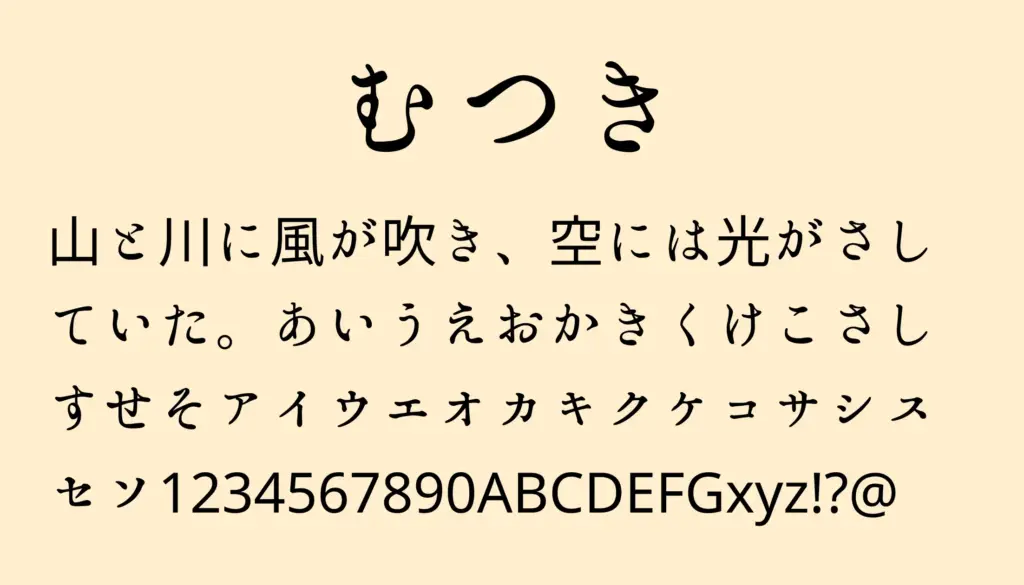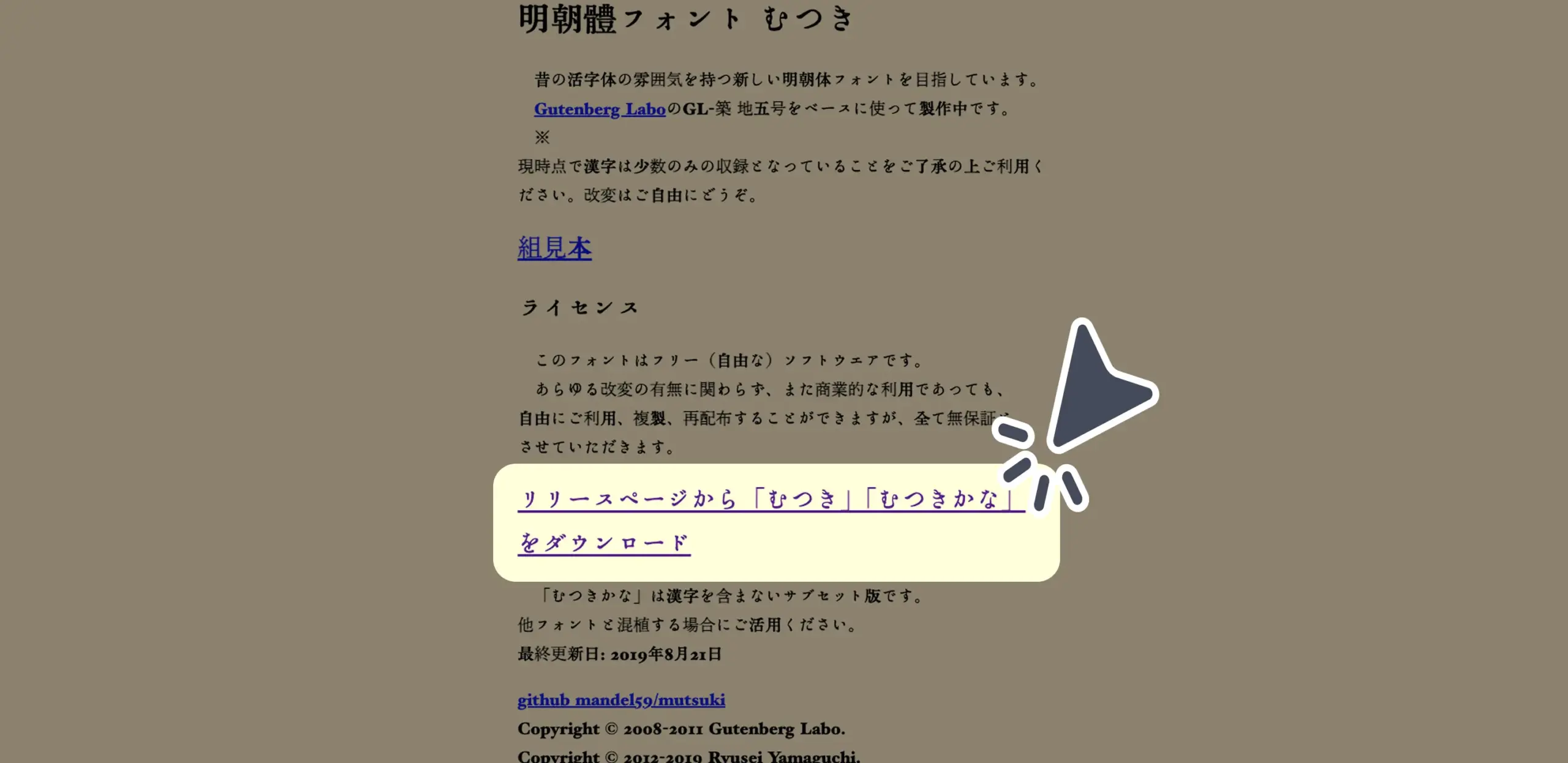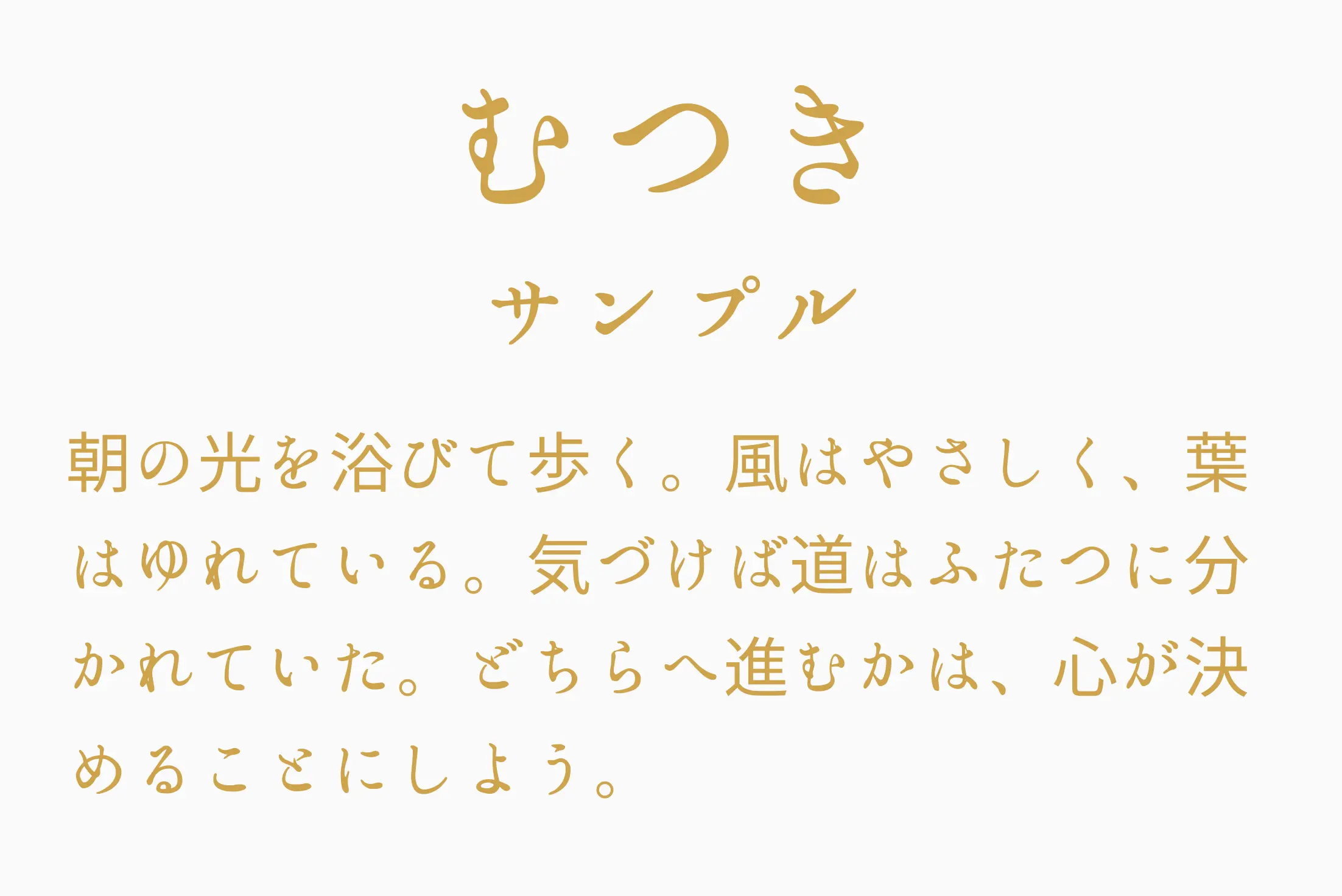
むつき 明治時代の活版印刷で使われていた「築地五号」の風合いを再現したクラシカルな明朝体フォントです。墨溜まりやかすれを活かしたデザインで、懐かしさと高級感を両立。和風・レトロ・伝統美を求めるデザインに最適です。 カテゴリ OS Windows/Mac OS 形式 OpenType 収録文字 ひらがな・カタカナ・英字・数字・記号 商用 商用利用可 配布サイト こちら ※利用規約は必ずお読みください フォントをダウンロードする 類似フォント一覧 白光明朝 ぎゃる文字ゴシック 水明、夏へきらめく 鳩とブリキのワンダランド 5x3pixel font(5×3ピクセル文字) ひとりゴシック 怪聞書 黒華明朝